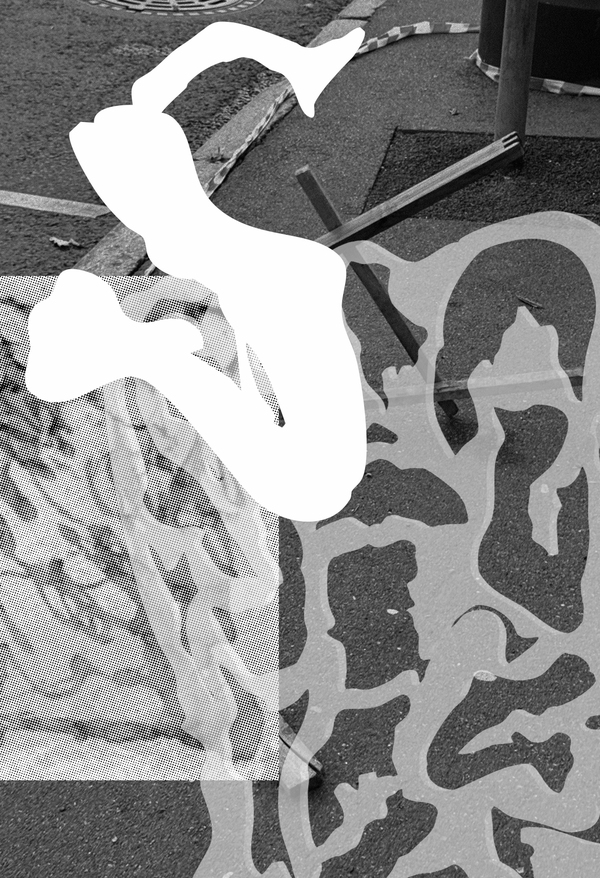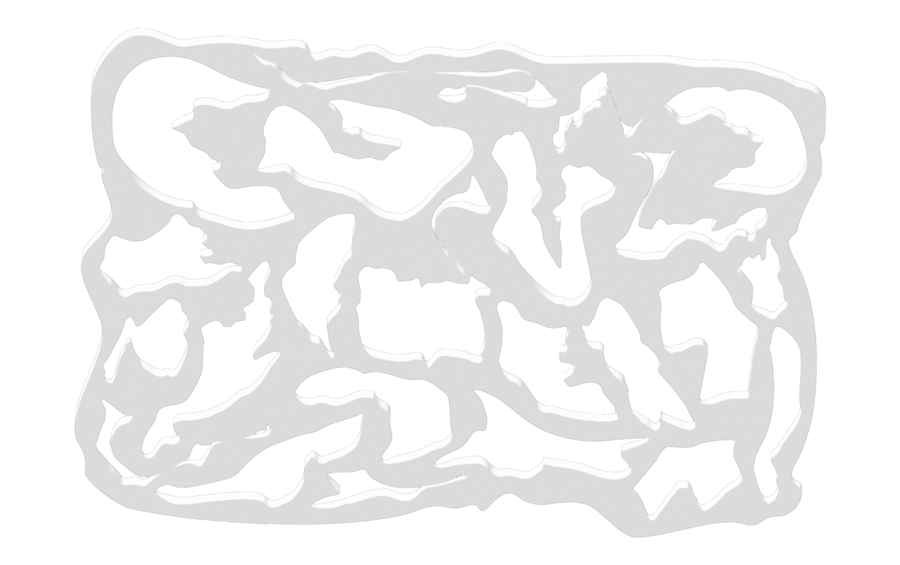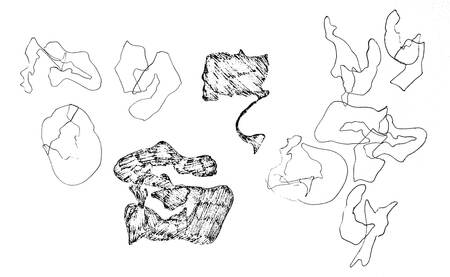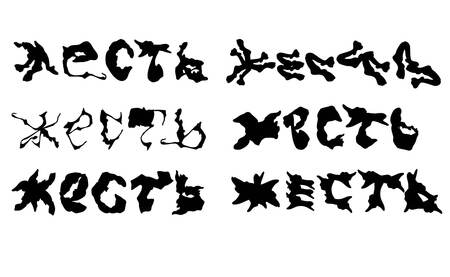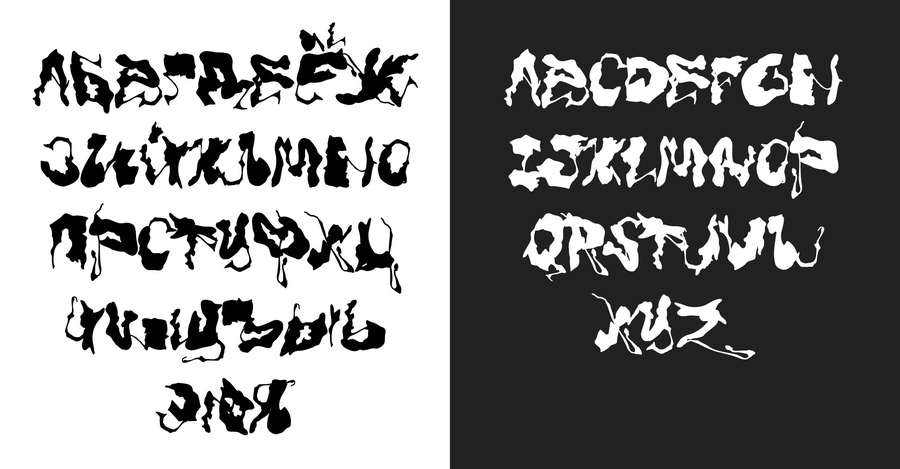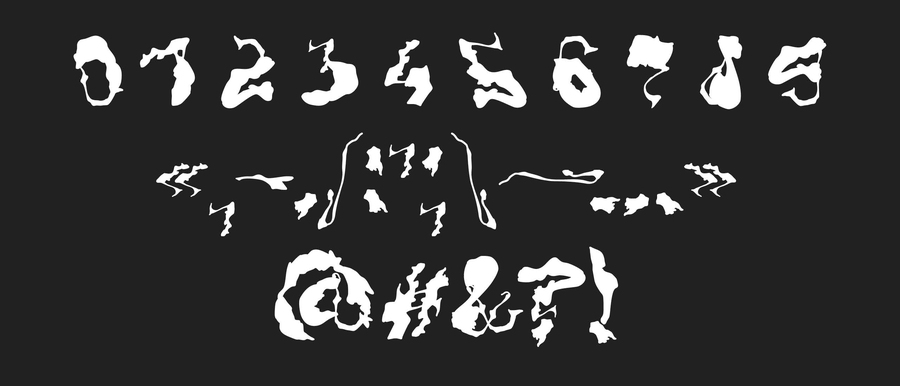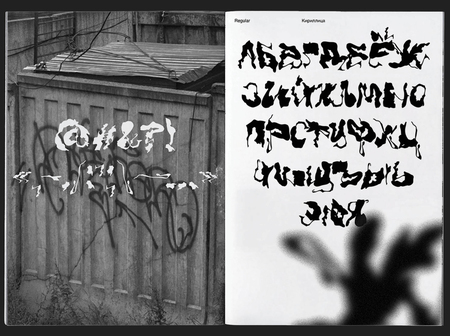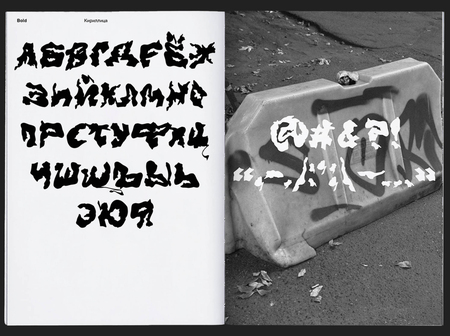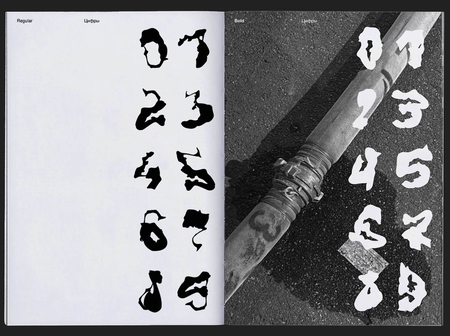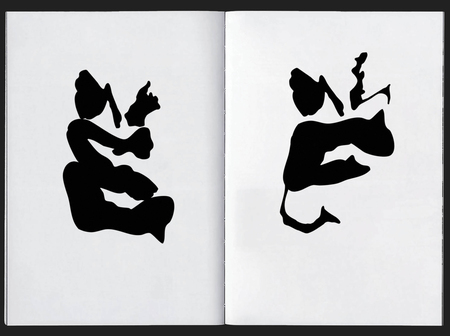
Scrap Typeface
Scrap Typeface — модульный шрифт с шумным, бунтарским характером, вдохновленный следами, оставшимися от сорванных объявлений. Он хаотичный и шероховатый, а в начертании bold ещё и напористый, громкий. Идеален для обложки вашего первого рэп-сингла.
Работа с модулями: поиск формы
Scrap Regular: Алфавит
Scrap Regular: Цифры и пунктуация
Regular: сочетание массивных и тонких форм, в каждой букве используются модули с тонкими линиями Bold: «тонкие» модули могут использоваться только для выносных элементов
Scrap Bold: Алфавит
Scrap Bold: Цифры и пунктуация